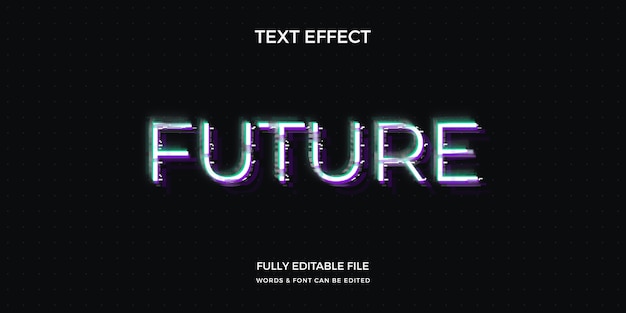
Реалистичный эффект текста с ошибками для текста видеоигр для редактируемого шрифта Cyber Monad vhs
Эффект динамического свечения и искажения текста. редактируемый текст и шрифт.